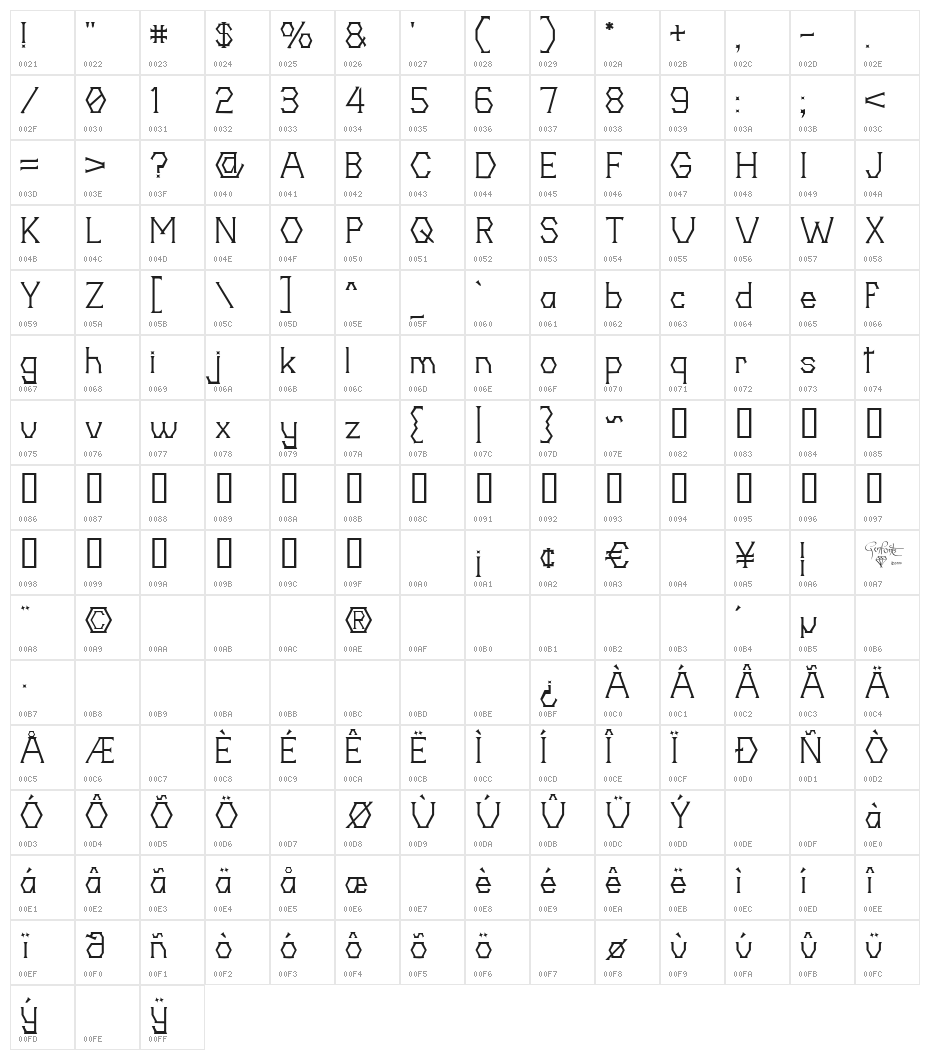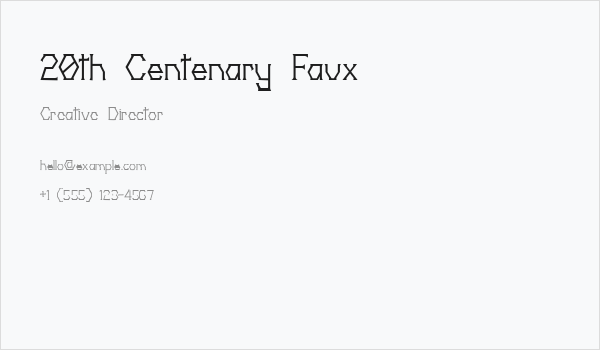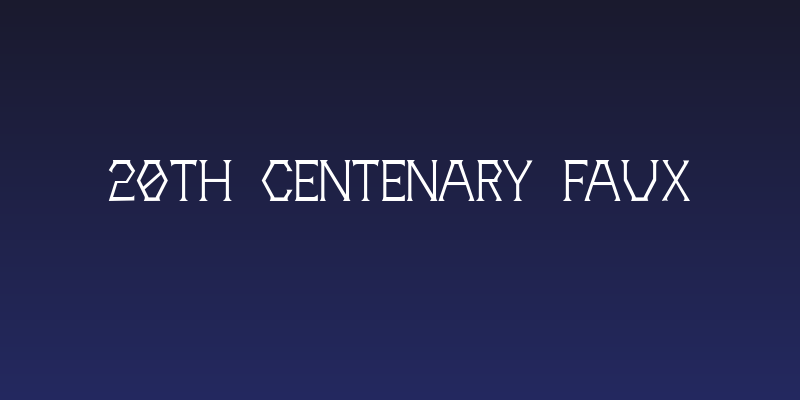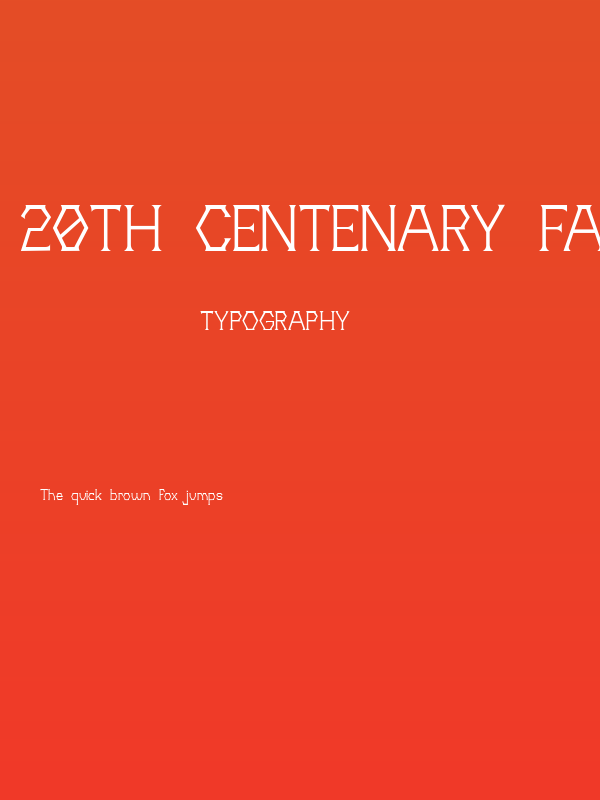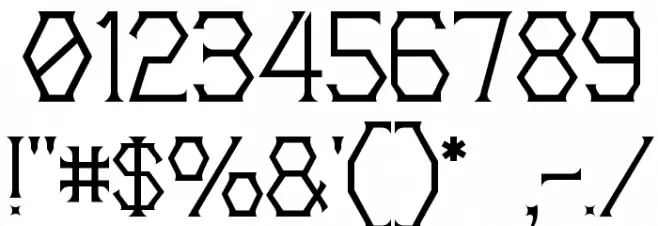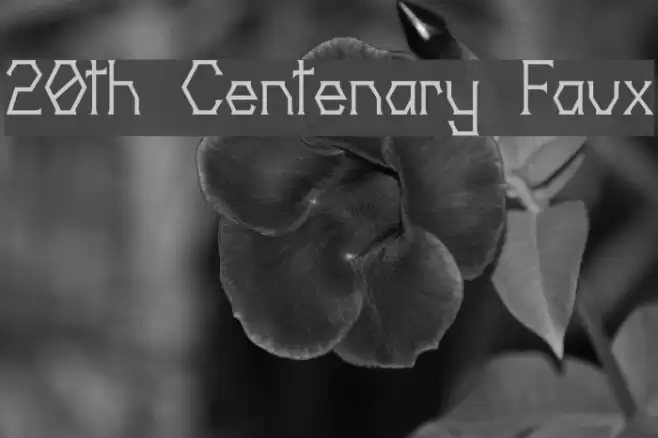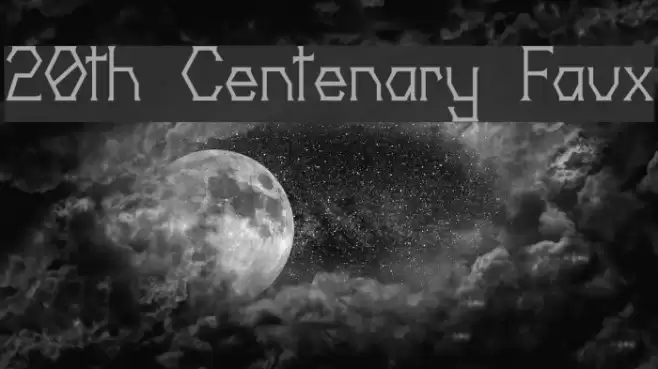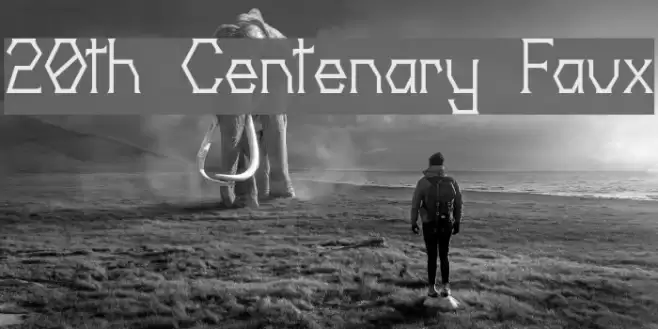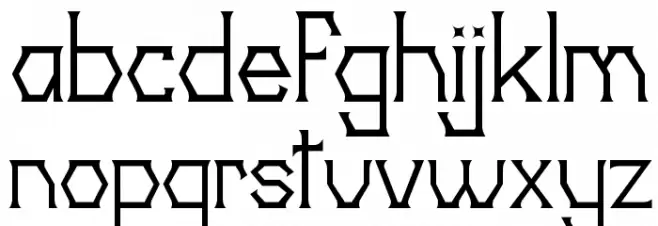
20th Centenary Faux Font
| उपयोग का मामला | Headlines, Logos, Posters |
| सुझाए गए प्रोजेक्ट | Ideal for sci-fi themed designs, modern branding, posters, and digital media that require a futuristic touch. |